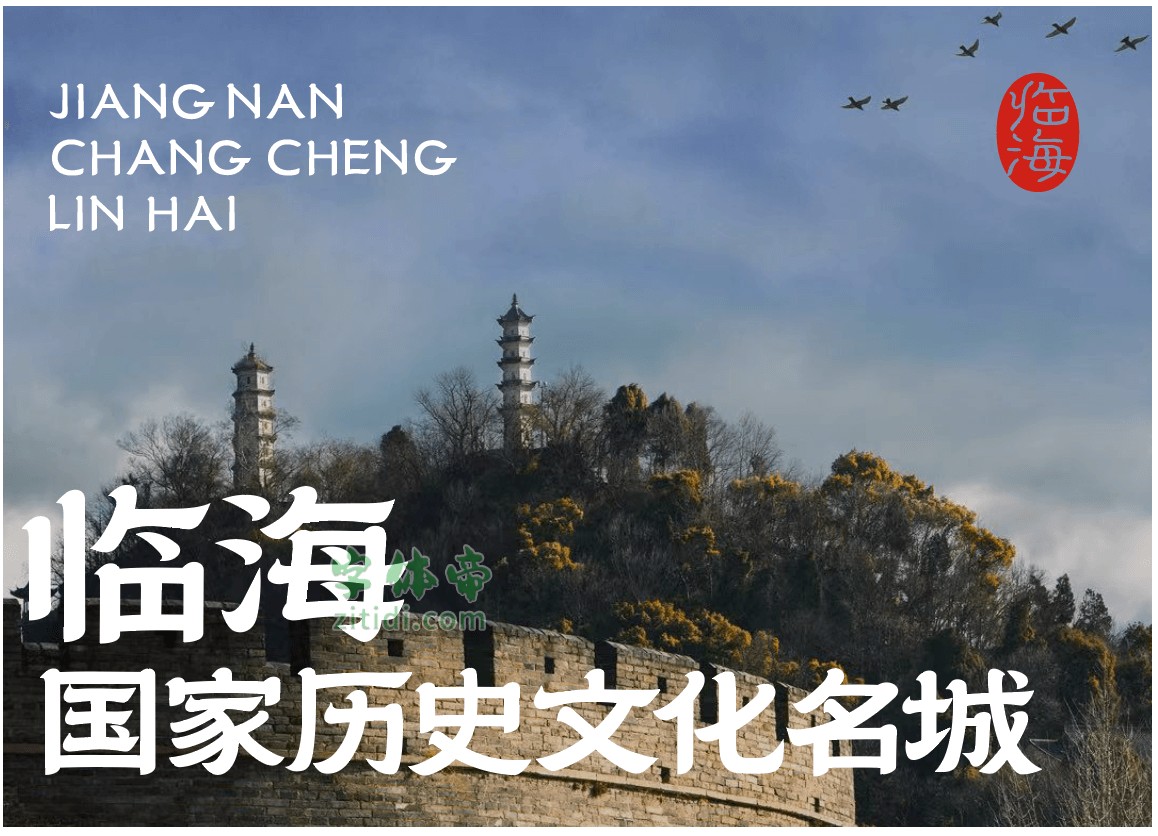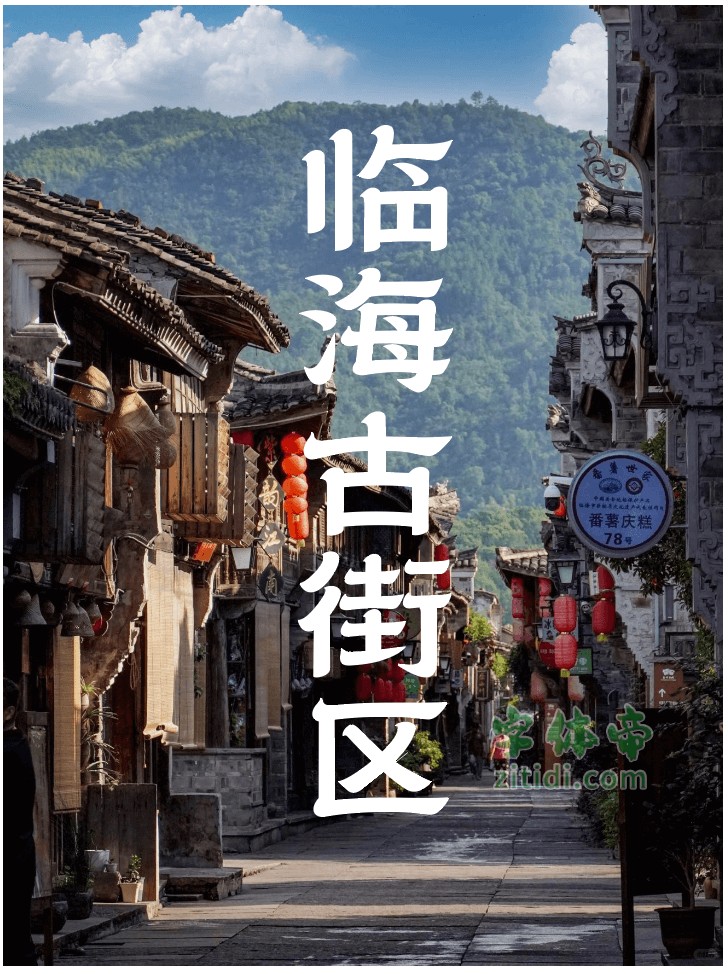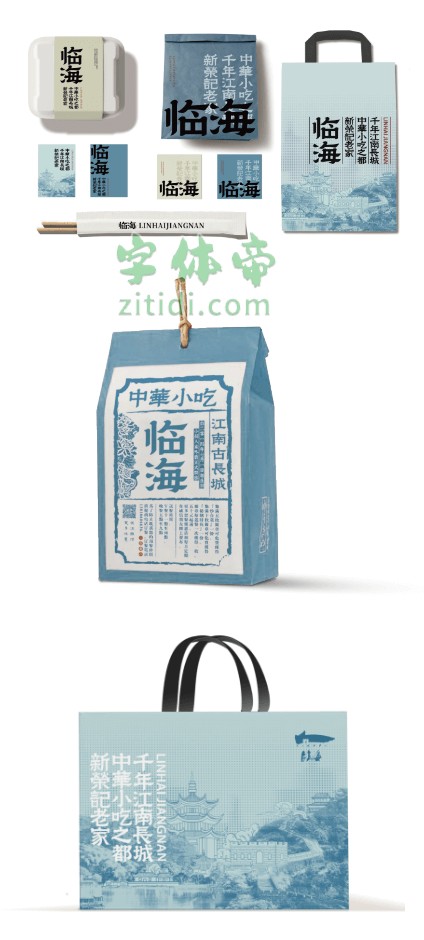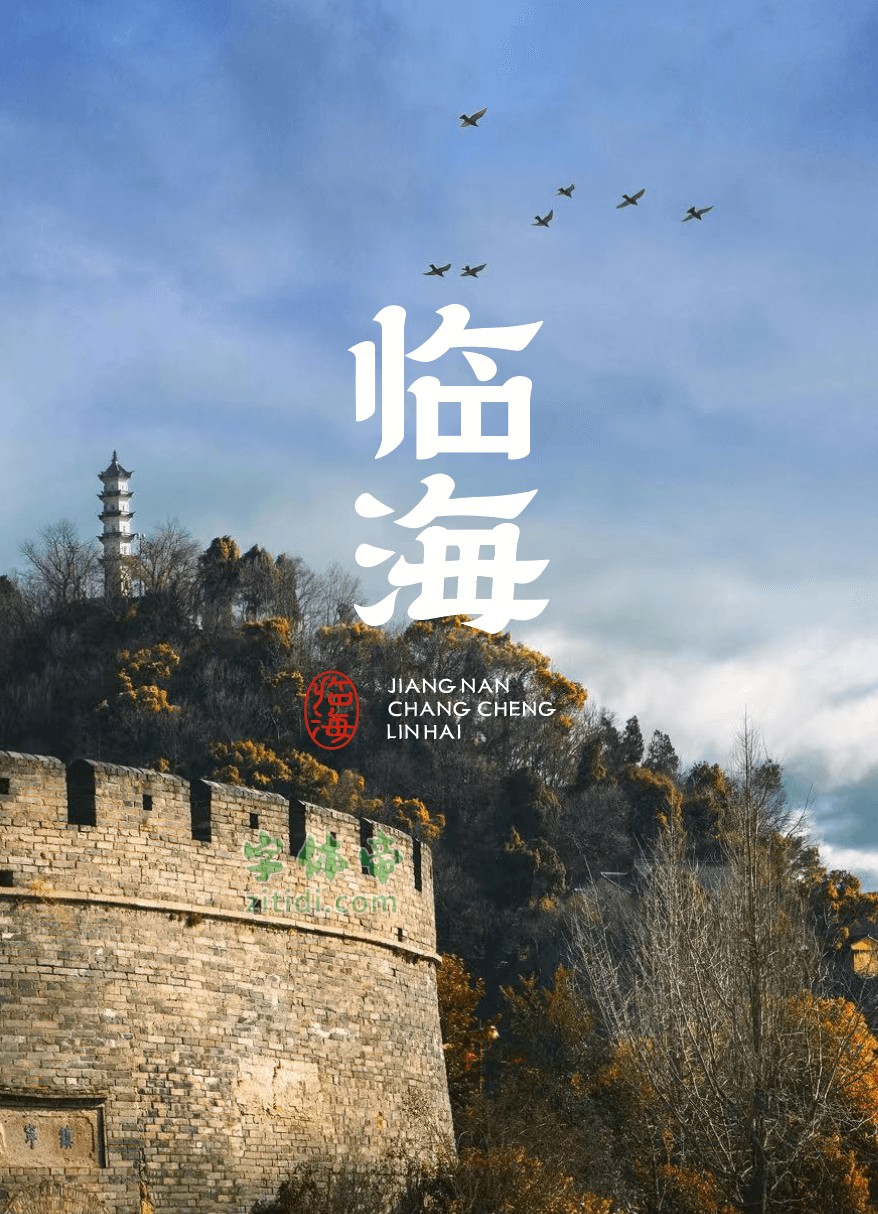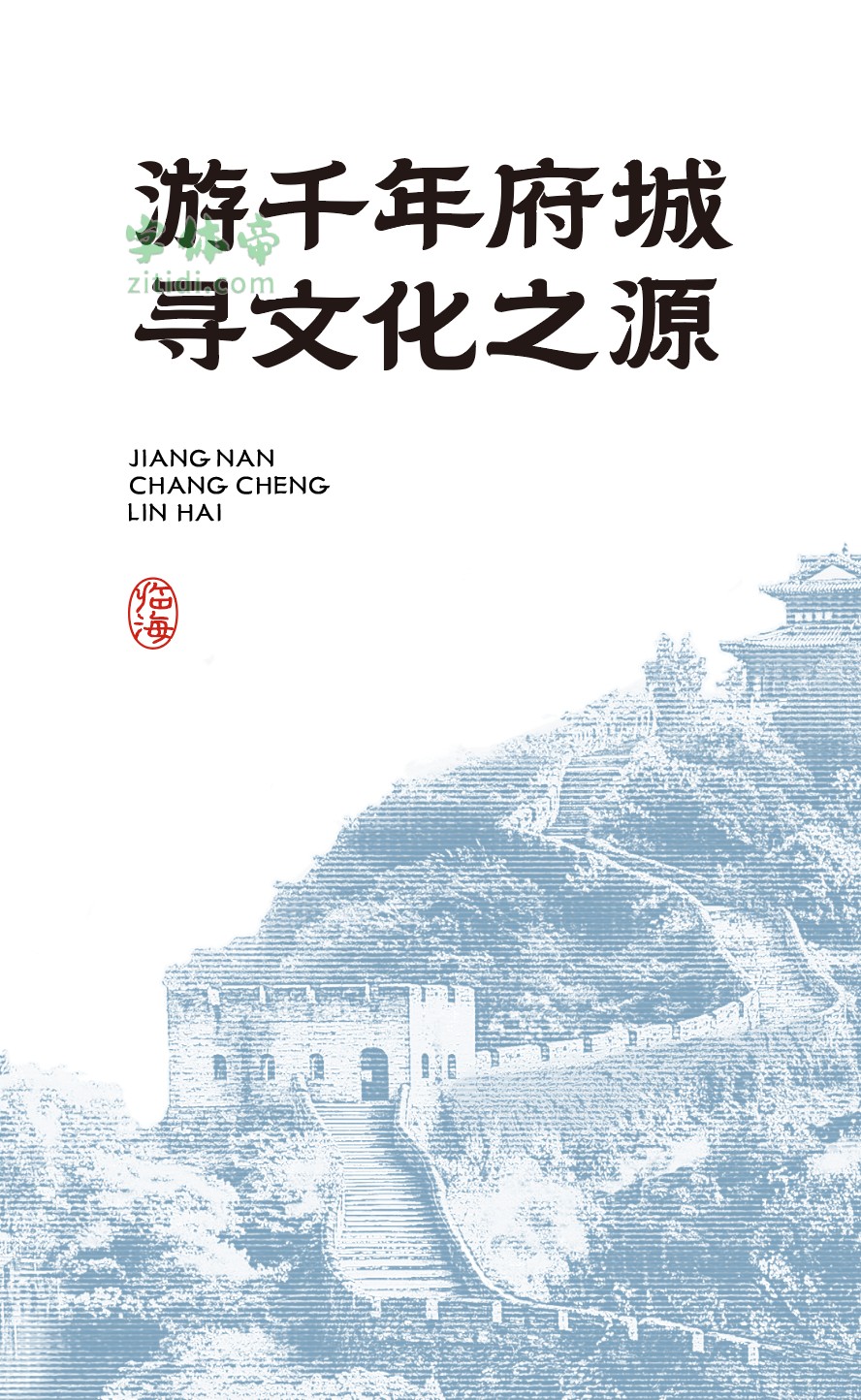
一座城市的影响力
取决于城市文化的影响力
经营城市品牌
经营的是一座城市的文化辨识度
……
为持续打响“千年台州府 江南真宋城”
文旅品牌形象
让文化传播更具辨识度
市社发集团积极谋划
深度挖掘临海文化内涵
与乡立方团队携手打造
推出了拥有临海独特风格和时代烙印的
专属字体
台州府城墙、龙兴寺、千年紫阳街等文化古迹星罗棋布骆宾王、戚继光、朱自清等叙说着临海文化绵长的故事文人舞墨,匠者筑基共同铸就了临海的文化底蕴正因如此临海能较早跻身于“国家历史文化名城”之列能有信心对世界说“千年古城,最忆临海”
历史底蕴深厚、文化资源丰富这是临海不可复制的独特禀赋但如何让世界认识临海呢源浚者流长,根深者叶茂文字是文化传承的标志临海字体更是传播临海文化的基础元素
一城化一字
一字如一城
站在时光的纵轴上向前望去
隶书的演变史
也是临海城市变迁的缩影
将千年古城、人文繁盛、山水之韵
等临海城市特质
结合汉字五大字体之一的隶书体
隶书,兴盛于汉代
也是临海城市起源的时代
隶书所具有的厚重、古典、拙朴特质
旷达雄浑,古朴内敛
将临海的城市特质展示的淋漓尽致
临海古城,也就是台州府城,始建于晋,扩建于唐,距今已有1600多年的历史。古城原有七门十三敌台,现仅存四门和四座敌台。
江南长城,是江南地区唯一的长城,城墙依山就势,俯视大江,敌楼林立,气势恢宏,是北方明长城的师范和蓝本,人称“江南八达岭”,现存近5000米,目前已列入世界文化遗产预备名单之中。
紫阳古街,全长1080米,是整个古城的中轴线,有“临海第一古街之称”,街道两边的房屋店铺雕梁画栋、古色古香,保留着宋代遗风、明清格局。
在这里,戚继光驰骋海疆“封侯非我意,但愿海波平”。在这里,骆宾王仗剑而起“宝剑思存楚,金锤许报韩”。“莫言沧海阔,杯度自应知”,最澄大师万里求法,化成千佛塔的“菩萨垂眉,万千悲悯”。
无论是临海词调、黄沙狮子、大石车灯、大田板龙、小芝鼓亭、上盘花鼓、城关细吹亭等传统民间文化艺术,还是糟羹、麦油脂、马蹄酥、羊脚蹄、麦饼、蛋清羊尾等传统风味小吃,亦或是刺绣、草编、竹木雕刻等传统工艺。
府城人民的智慧,凝结于千家万户的烟火之中,汇集成千年临海的独特画卷。
通过临海字体打造临海符号化IP将临海字体融入到城市的历史、文化、形象、资源、产品、内容等各个层面让临海字体成为这座城市具有独特辨识度和人格化的城市品牌